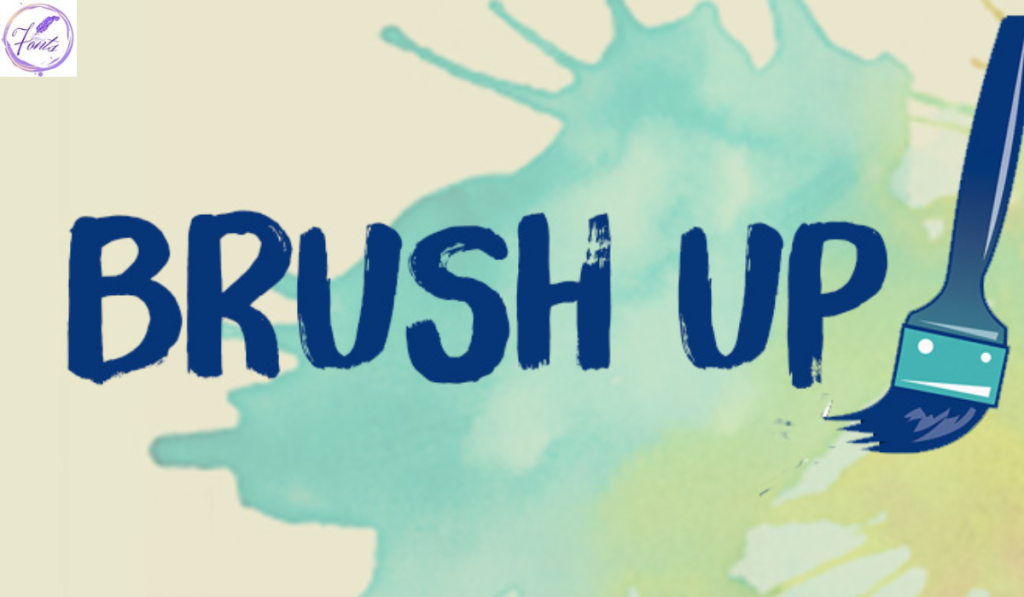
Font Brush Up việt hóa
Tác giả: Monotype Corporation
Ngày phát hành: 1955
Ngôn ngữ: Tiếng Việt, nhiều ngôn ngữ khác
Bộ Font: Brush Up
Phân loại: Cá tính, độc đáo
Kiểu chữ: Không chân
Font brush up là một bộ font độc đáo và sáng tạo, được thiết kế để mang lại vẻ đẹp tự nhiên và phóng khoáng cho các dự án thiết kế của bạn. Font này được tạo ra bởi một nhóm các nhà thiết kế tài năng, với mục tiêu tạo ra một kiểu chữ mang phong cách vẽ tay mượt mà và tinh tế. Font brush up đặc biệt phù hợp cho các dự án cần sự năng động và sáng tạo như thiết kế logo, bìa sách, poster và các sản phẩm quảng cáo. Với phiên bản Việt hóa, font brush up càng trở nên gần gũi và dễ sử dụng cho người dùng Việt Nam.
Đánh giá font brush up
Font brush up nhận được rất nhiều lời khen ngợi từ các chuyên gia thiết kế. Điểm nổi bật của font này là nét chữ mềm mại nhưng vẫn giữ được sự mạnh mẽ và rõ ràng. Các nhà thiết kế đánh giá cao sự linh hoạt của font brush up, khi nó có thể dễ dàng điều chỉnh để phù hợp với nhiều phong cách thiết kế khác nhau. Font này không chỉ đẹp mắt mà còn rất dễ đọc, giúp truyền tải thông điệp một cách hiệu quả. Với những đặc điểm nổi bật này, font brush up đã trở thành lựa chọn yêu thích của nhiều nhà thiết kế trên toàn thế giới.